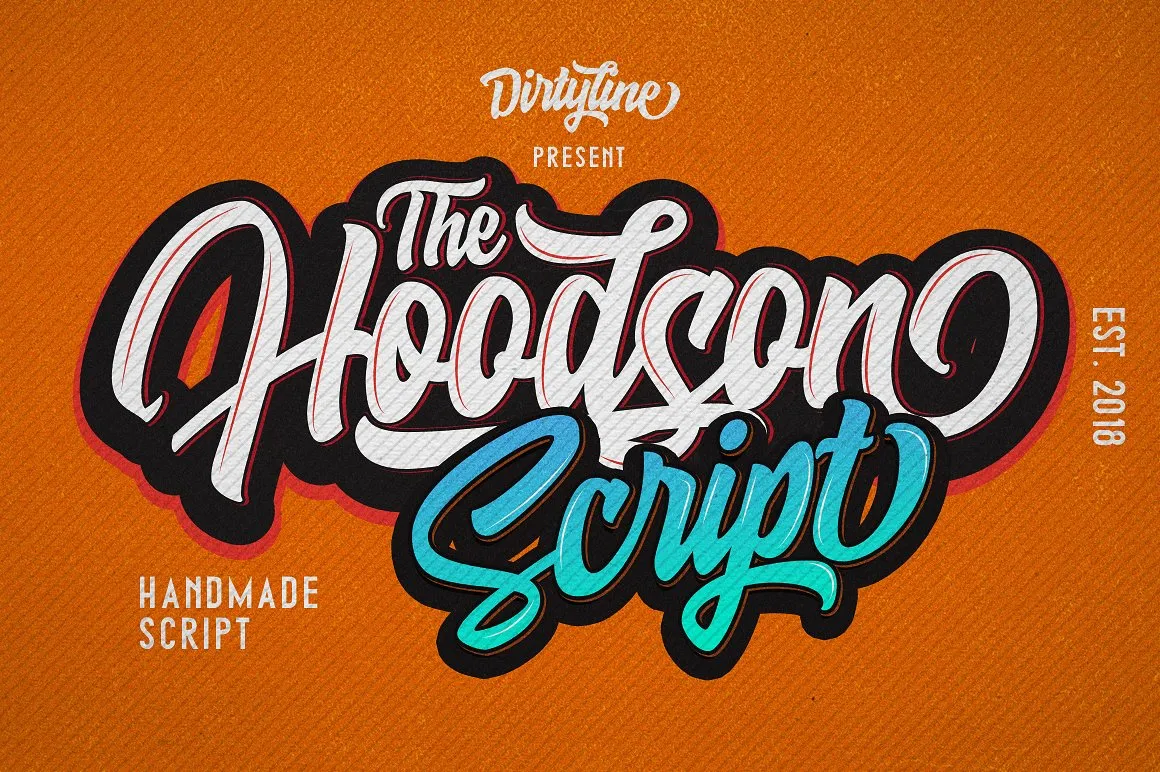
A Hoodson Script é uma elegante fonte tipo script moderna e autoral, criada pelo estúdio Dirtyline Studio. Inspirada nos estilos retro e letra à mão, essa fonte oferece um padrão de base muito suave, tornando-a perfeita para uso em logotipos, citações escritas a mão, embalagens de produtos, cabeçalhos, cartazes, merchandising, mídias sociais e cartões de agradecimento. Uma das suas principais características é o conjunto de fontes alternativas incrivelmente útil que acompanham a Hoodson Script: uma fonte de marcador perfeitamente compatível, além de um conjunto super conveniente de swashes. Este conjunto único oferece muito mais flexibilidade e personalização nas criações, tornando-a um recurso indispensável para designers. Ideal para os mais criativos entre nós, a Hoodson Script é certamente uma adição que vai deixar seu trabalho de design impecavelmente autêntico e moderno.